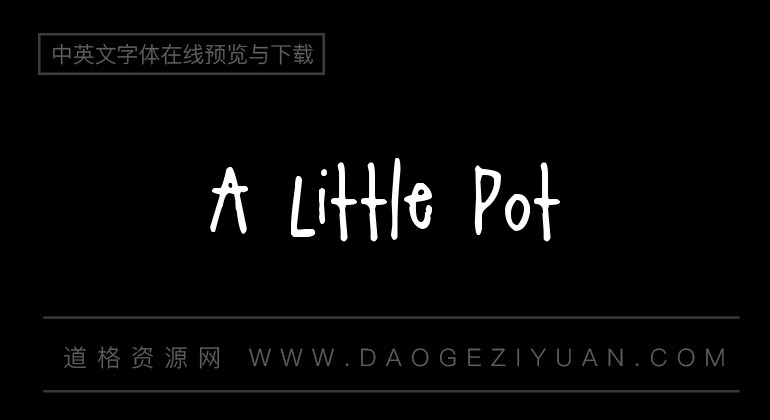
? A Little Pot是一款非常可爱的字体,由著名的设计师David Rakowski设计。它的特点是拥有温暖的风格,每个字母都带有一点古朴的气息,让人感觉很舒服。它的字形也很特别,有着柔和的线条,十分适合用来制作漂亮的文字图案或者插画。内容介绍
A Little Pot是一款非常不错的手写艺术字体,具有很好的视觉感,适合于文化类的宣传设计、商业类品牌的广告和产品包装设计以及个性化文字排版等较多场景。